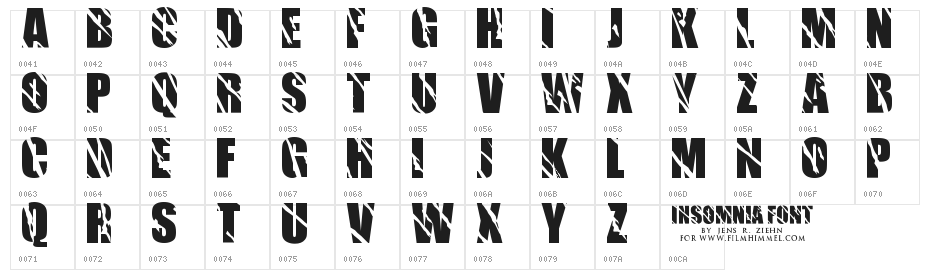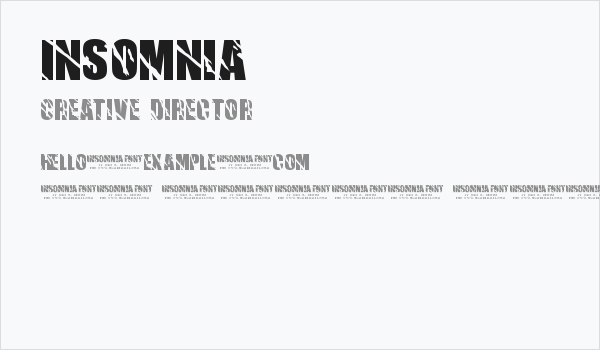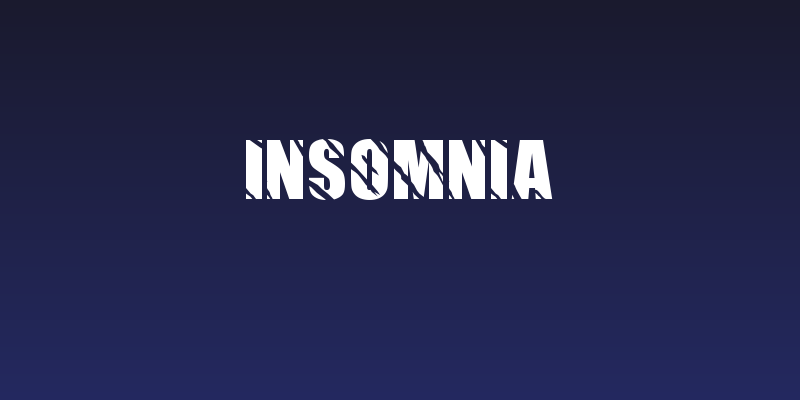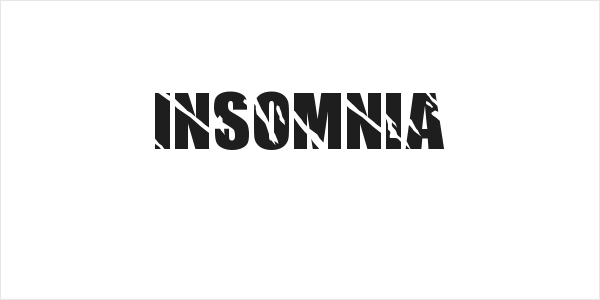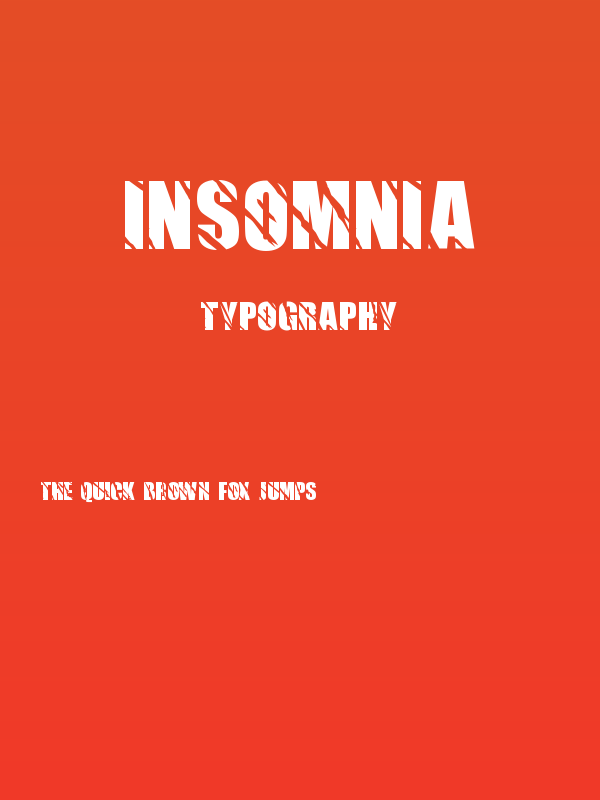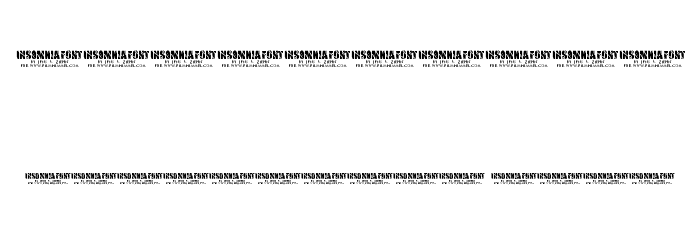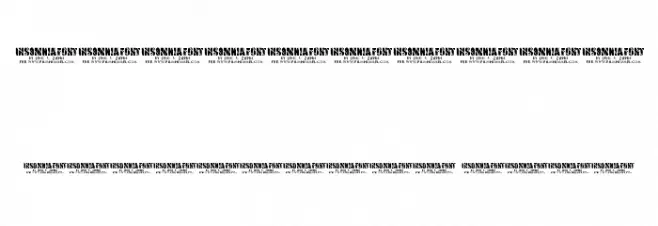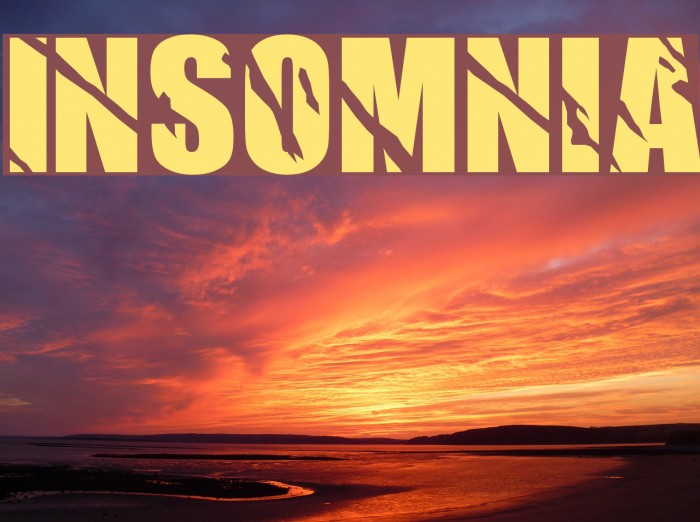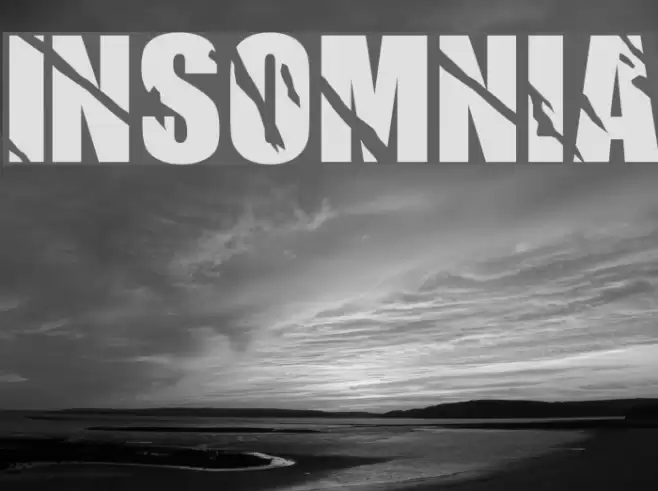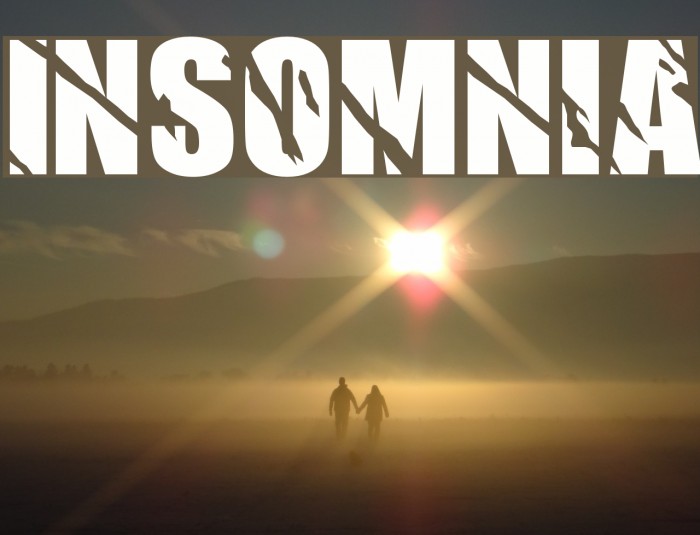
Insomnia Font
Fonts by Jens R. Ziehn - www.filmhimmel.com
| Estilo geral | Modern, Grunge |
| Projetos propostos | Ideal for music album covers, edgy posters, streetwear branding, and any project needing a rebellious or urban vibe. |